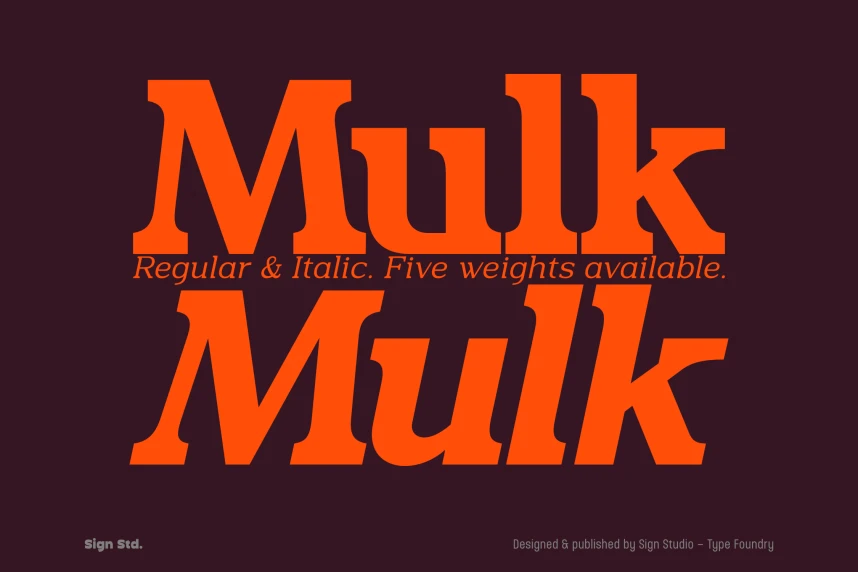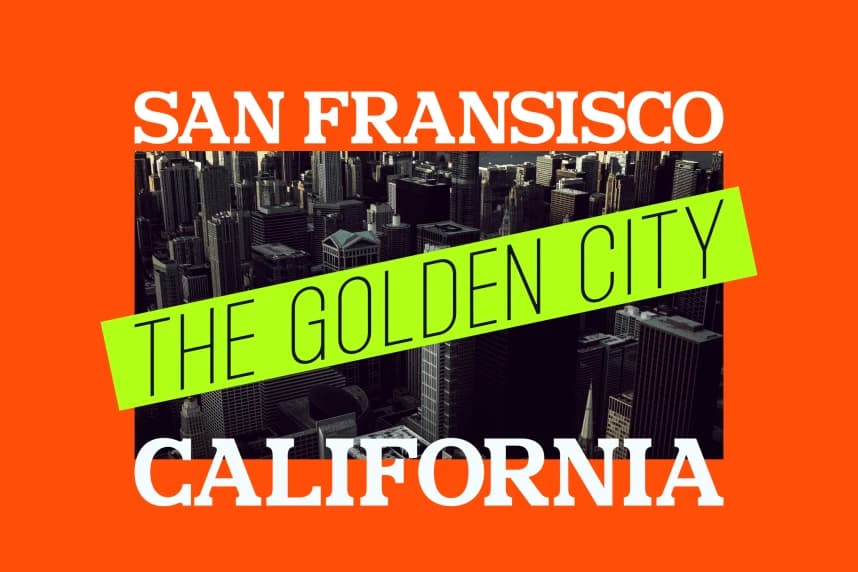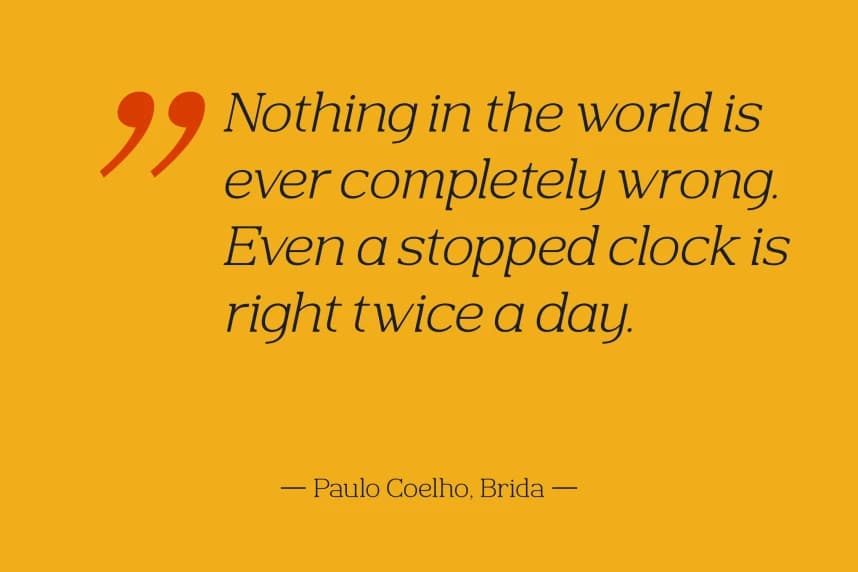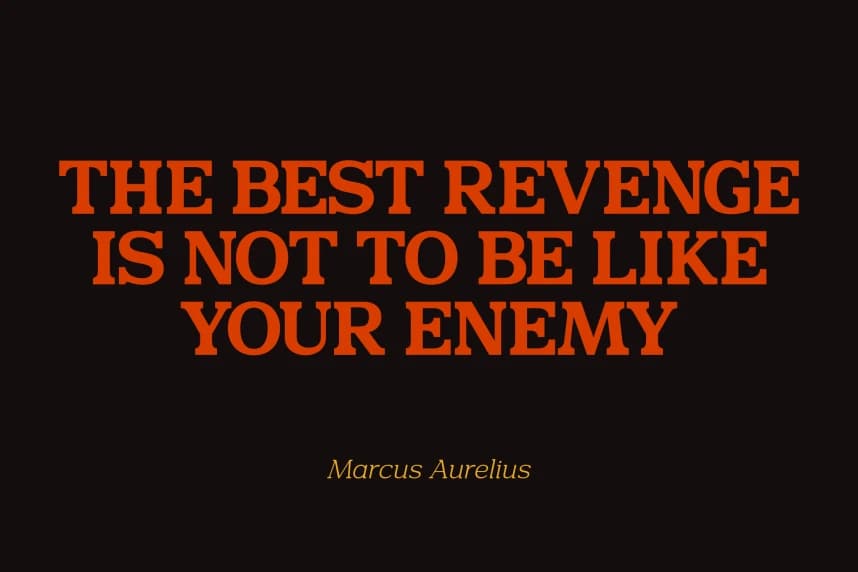
Mulk Slab Serif Font
Mulk Slab Serif Font, slab serif tipografisinin çağdaş bir yorumu olup modern bir dokunuşa sahiptir; daha geniş oranlar, güçlü slab serifler ve hafif daha yüksek stresli eğriler ile tanımlanır.
Mulk Slab Serif Font, slab serif tipografisinin çağdaş bir yorumu olup modern bir dokunuşa sahip; daha geniş oranlar, sağlam slab serifler ve hafifçe daha yüksek stresli eğrilerle karakterizedir.